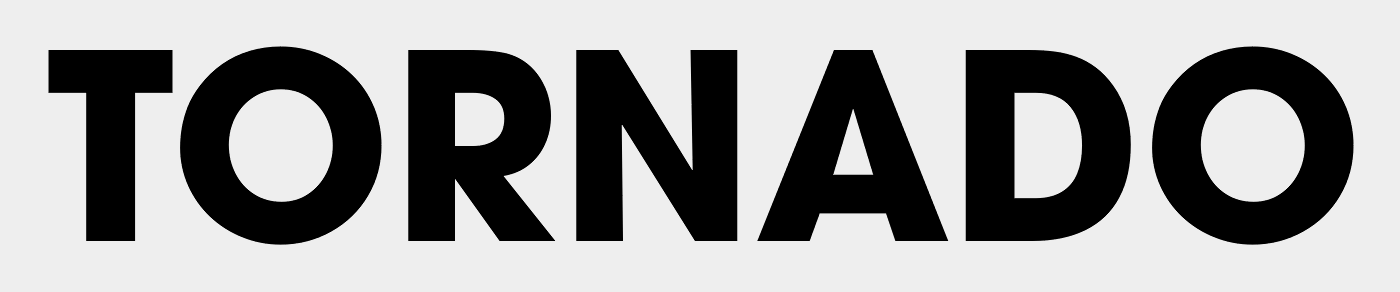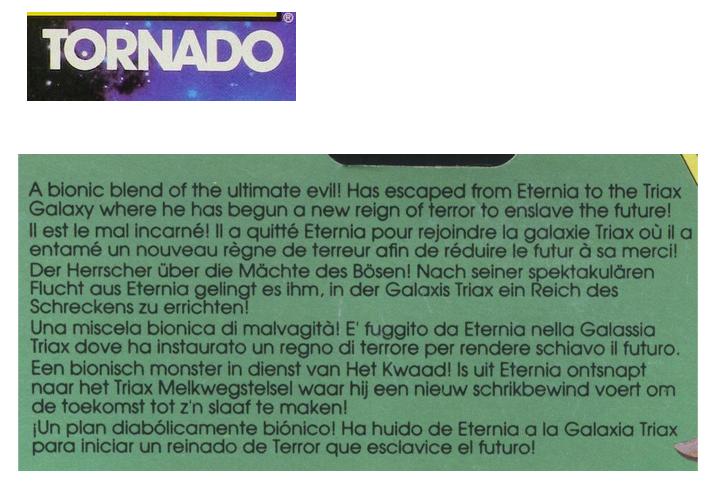
Schriftart von 80er Actionfigur gesucht
ich suche schon länger die Bezeichnung/Namen der nachfolgenden Schriftarten und würde mich sehr freuen, wenn mir da jemand weiterhelfen kann. Es handelt sich um die große weisse Schrift in Großbuchstaben und die Schriftart des Textes im grünen Rahmen. Evtl. ist es ja auch dieselbe?
Ich tippe mal auf die Avant Garde Gothic …
Vielen lieben Dank schon mal. Hier nochmal (gleiche Schriftarten) eine größere Alternative.
Und Avant Garde war lange die Standard-Schriftvorgabe von CorelDraw, das zudem das Zusammenschieben der Buchstaben auch sehr erleichtert:
einfach am Anfasser rechts unten schieben.